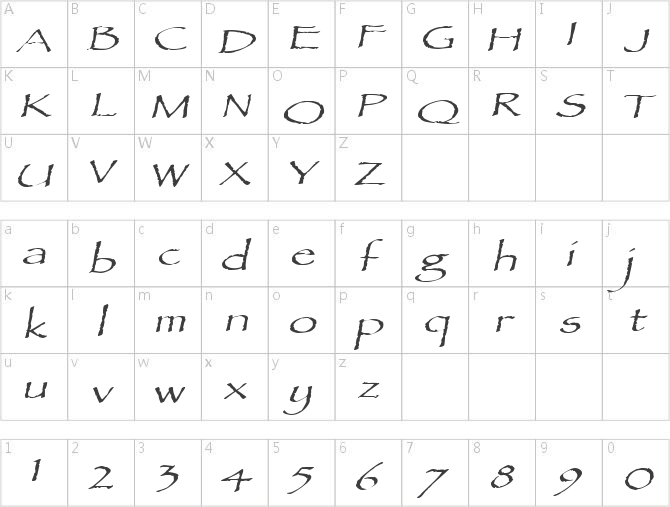
字體名稱: ancient
ancientscriptextendeditalic
ancientscriptextendeditalic介紹
ancientscriptextendeditalic字體字庫是一款讓人賞心悅目、百看不厭的英文字體,適合各類廣告和產品包裝設計應用,字體大小0.07MB,格式為ttf字體,上傳用戶是/zyj【GF】,作者/版權方為未知